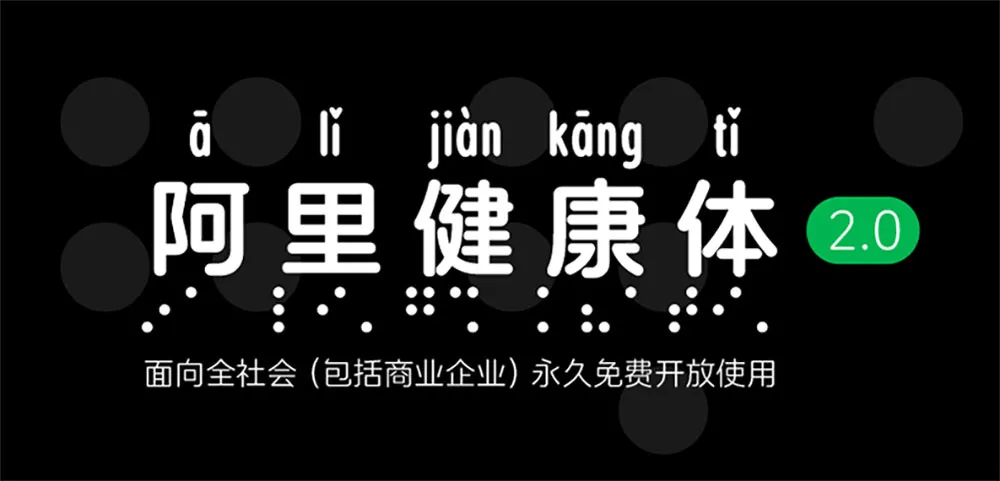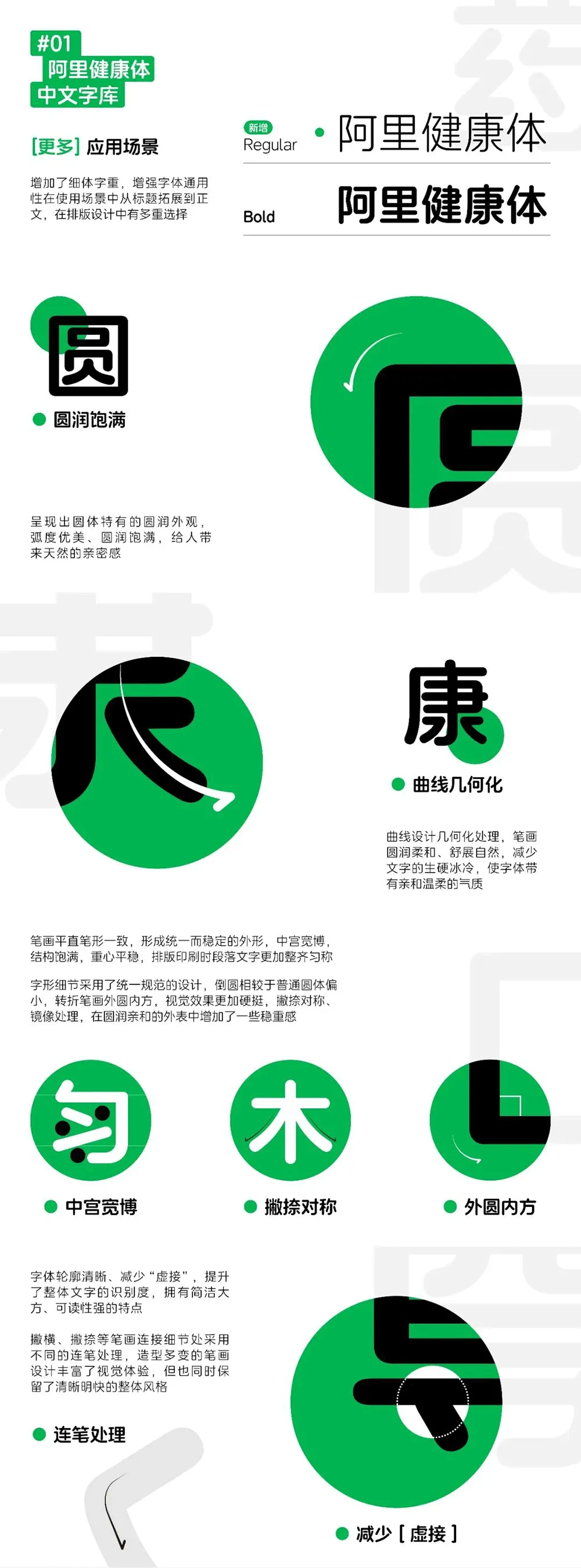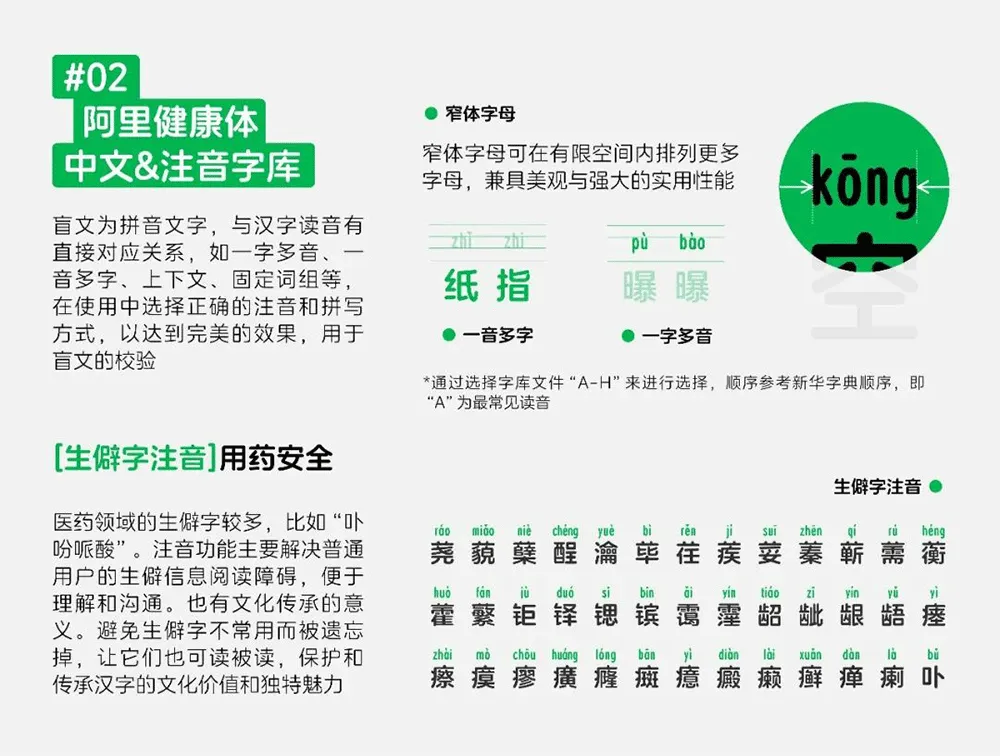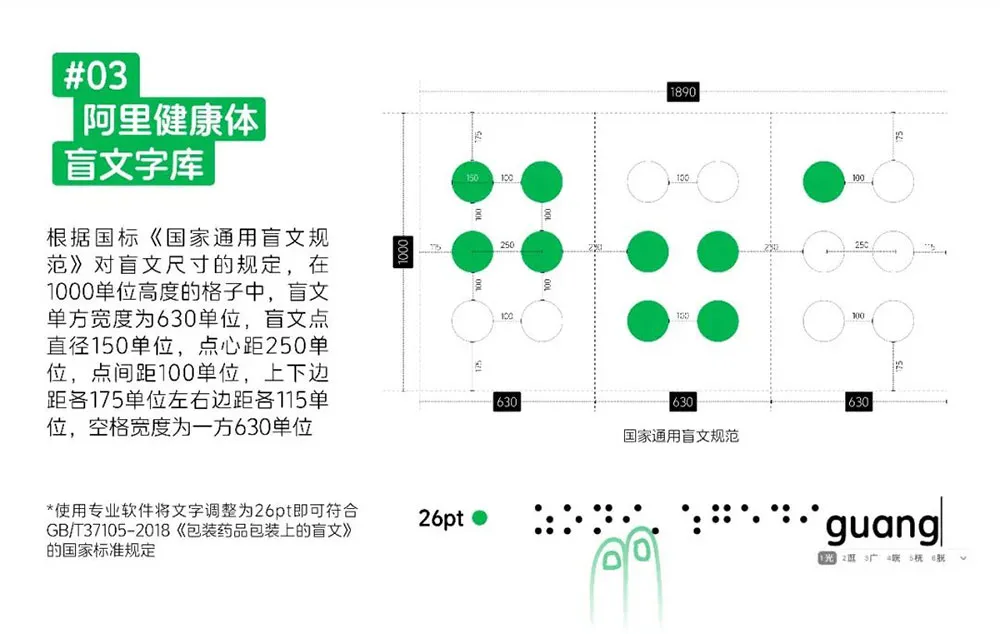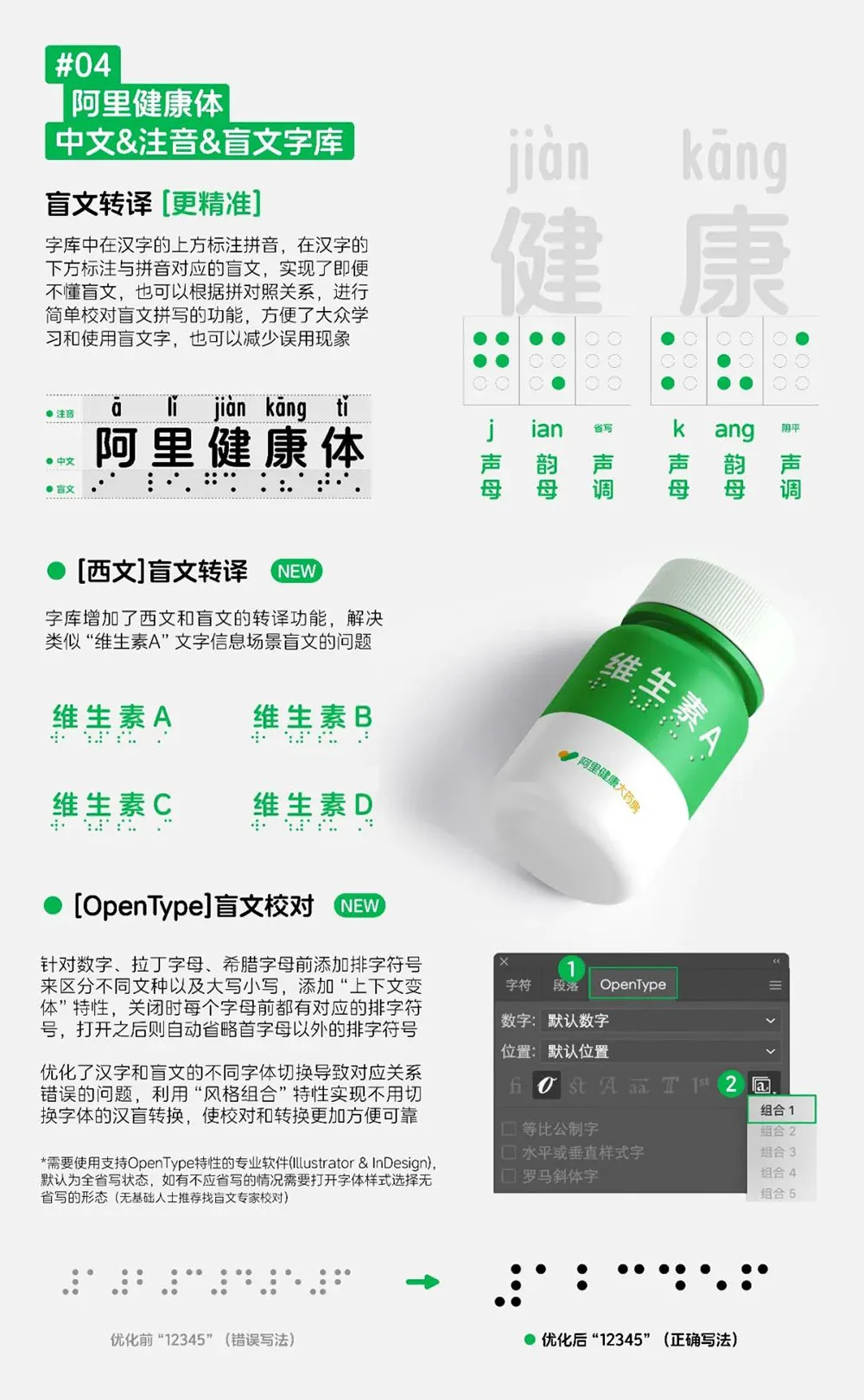
2023年11月,由阿里健康設計與方正字庫共同設計開發的阿里健康體2.0家族字體正式發佈。該字體以無障礙設計為初衷,以服務於視障人士為目標,是首款中文盲文注音定製字體。為了鼓勵更多人關注無障礙設計,進一步推進醫療健康服務的普惠可及,阿里健康體2.0面向全社會(包括商業企業)永久免費開放使用,希望通過技術公益,推動無障礙環境建設,傳遞現代設計的人文關懷。
基於阿里健康有溫度的關懷感的品牌定位,以及為了保持更好的文化承接性,在原始標誌字體圓體風格的基礎上,設計師統一了筆畫特徵,使字體更加規範和諧。筆畫多以幾何化處理方式,讓字形看上去更加嚴謹端莊,符合阿里健康醫療行業的品牌屬性。阿里健康體廣泛應用於品牌文化展示、廣告宣傳以及物料印刷等整套視覺系統中。
此款字體是國內首款服務於視障人士的中文盲文注音定製字體,解決藥品及產品包裝上盲文、生僻字使用問題,為視障人士搭建一座溝通世界的橋樑。筆畫多以幾何化處理方式,讓字形看上去更加親和有溫度。
針對藥品名生僻字認讀障礙問題,以及關注弱勢群體用藥問題,本次阿里健康體添加了注音字庫和盲文注音字庫,以方便藥品生產各個環節參考應用,同時呼籲社會關注弱勢群體,為他們送去關懷與溫暖。